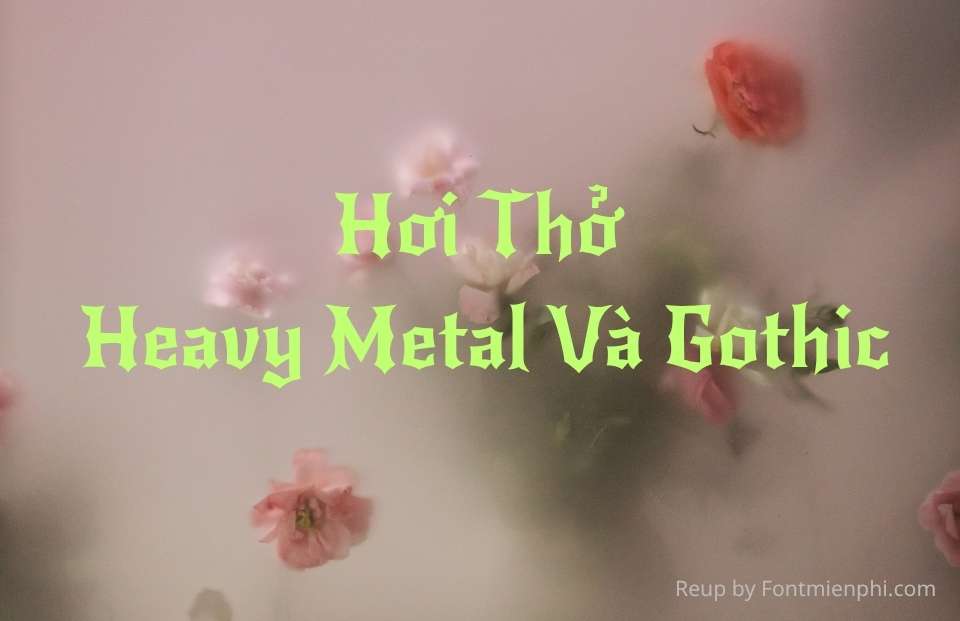
Font Việt Hóa SQT Newrocker – Hơi Thở Heavy Metal Và Gothic Đầy Máu Lửa
Khám Phá Font Việt Hóa SQT Newrocker – Hơi Thở Heavy Metal Và Gothic Đầy Máu Lửa
Chào mừng các chiến hữu đam mê sự gai góc và mạnh mẽ! Nếu những phông chữ mềm mại, thanh lịch không đủ để diễn tả cá tính bùng nổ trong dự án của bạn, thì hôm nay Font Miễn Phí mang đến cho bạn một “vũ khí hạng nặng” thực sự: Font Việt hóa SQT Newrocker. Đây là bản tuyên ngôn bằng chữ viết dành riêng cho những thiết kế mang tinh thần nổi loạn, u tối và đầy gai góc.
Font Việt Hóa SQT Newrocker : Khi Âm Hưởng Heavy Metal Trở Thành Nghệ Thuật Chữ
Được truyền cảm hứng từ những logo của các ban nhạc Rock/Heavy Metal đình đám và nghệ thuật xăm hình (Tattoo lettering), Newrocker không phải là một phông chữ dành cho sự thỏa hiệp.
1. Đường Nét Gai Góc, Mang Đậm Chất Gothic
SQT Newrocker sở hữu một diện mạo vô cùng “hầm hố”. Các chữ cái được thiết kế với những nét cắt chéo dứt khoát, góc cạnh sắc nhọn và hơi hướng bất đối xứng mang đậm phong cách Blackletter (chữ Gô-tích cổ). Nó tạo ra một cảm giác rách rưới, bụi bặm nhưng lại cực kỳ cuốn hút, giống như những bản nhạc Rock gào thét đầy năng lượng.
2. Dấu Tiếng Việt Được Xử Lý Ấn Tượng Bởi SQT
Điểm khó nhất khi Việt hóa các phông chữ có độ gai góc cao chính là làm sao để thêm dấu mà không làm mất đi cái “chất” thô ráp ban đầu. Phiên bản SQT Newrocker đã làm rất xuất sắc điều này:
• Bộ dấu sắc lẹm: Các dấu thanh (sắc, huyền, hỏi, ngã, nặng) và dấu mũ được thiết kế đồng điệu hoàn toàn với các góc nhọn của chữ cái gốc.
• Không phá vỡ cấu trúc: Khoảng cách (kerning) được tinh chỉnh để ngay cả khi bạn gõ những cụm từ Tiếng Việt dài, văn bản vẫn giữ được một khối thống nhất, dày dặn và mạnh mẽ.
3. “Sân Khấu” Tỏa Sáng Của Font Việt Hóa SQT Newrocker
Với cá tính áp đảo, đây là một Display Font (phông chữ hiển thị) tuyệt vời cho các dự án cần sự phá cách cực độ:
• Âm nhạc & Sự kiện: Thiết kế poster, cover album, banner cho các show diễn Rock, Metal, Indie hoặc các sự kiện Halloween, lễ hội ma quái.
• Thời trang Streetwear: Tạo logo hoặc in ấn lên áo thun (T-shirt typography) cho các local brand theo đuổi phong cách Darkwear, Grunge hoặc Punk.
• Gaming & Tattoo: Hoàn hảo cho giao diện các tựa game hành động, kinh dị, hoặc làm mẫu chữ tham khảo cho các nghệ sĩ xăm hình.